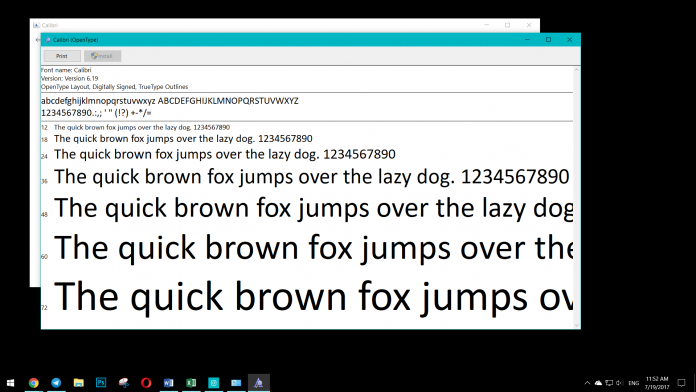
През 2015 година стана известна аферата „Панамски документи“: огромна колекция от 11,5 милиона документа с информация за над 200 000 офшорни сметки.
Панамските документи предизвикаха огромен резонанс в целия свят и доведоха до сериозни политически промени в някои страни и една от тях е Пакистан. Членовете на семейството на премиера Наваз Шариф бяха замесени в голям корупционен скандал и пакистанските власти започнаха активно разследване, в което важна роля изигра фирменият шрифт на Microsoft – известният на всички Calibri.
Притежаването на офшорни сметки не е незаконно, но те често се използват за пране на пари и неплащане на данъци. Името на самия Шариф го няма в Панамските документи, но иманата на неговите деца са там. Образувана е специална комисия, която много активно разследва и в рамките разследването проследява паричния поток и търси нарушение на закона.
За да защити по някакъв начин своето семейство, дъщерята на Наваз Шариф, Мириам Наваз публикува копия на документите, които би трябвало да опровергаят връзката на нейното семейство с тази афера. Но Мириам изпусна един важен момент – шрифтът на тези документи.
Разследващите публикуваха официално изявление, че новите документи са фалшиви, понеже те са датирани през 2006 година, но са написани на шрифта Calibri, представен на обществеността чак през 2007 година с новото поколение Microsoft Office.
Мириам отрича фалшифицирането, а разследването ще покаже, дали шрифтът на Microsoft ще изиграе ключова роля.